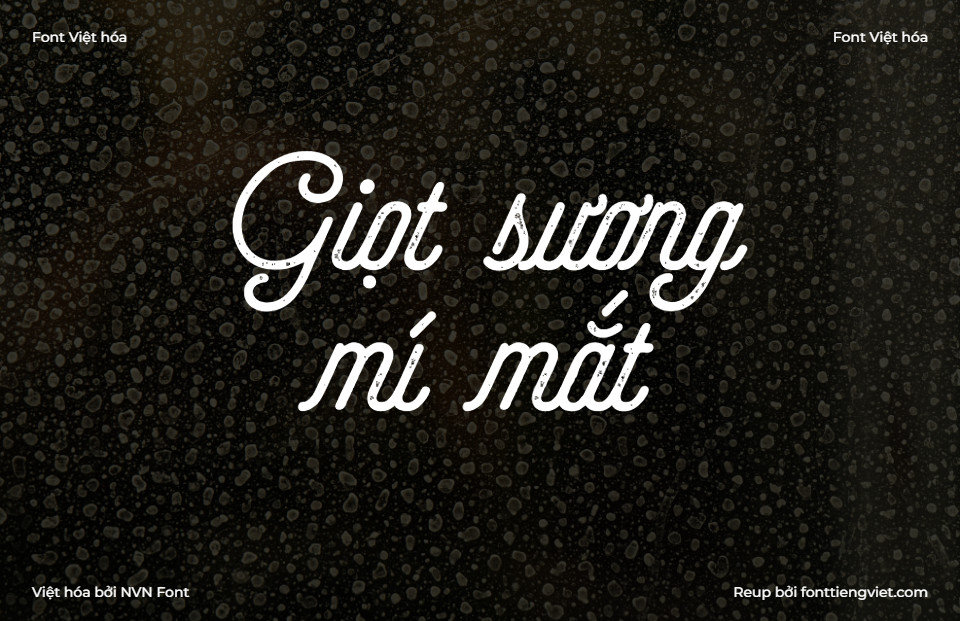
Font Việt hoá NVN Selfie Extra Bold Printed
Font Việt hoá NVN Selfie Extra Bold Printed: Đỉnh cao thiết kế cổ điển và mạnh mẽ
Giới thiệu về Font Việt hoá NVN Selfie Extra Bold Printed
Trong thế giới đồ họa hiện đại, việc tìm kiếm một bộ Font Miễn Phí chất lượng để truyền tải thông điệp là vô cùng quan trọng. Một trong những cái tên nổi bật đang được giới sáng tạo săn đón chính là Font Việt hoá NVN Selfie Extra Bold Printed. Đây là một biến thể đặc biệt thuộc gia đình Selfie, một bộ phông chữ lấy cảm hứng từ những tấm biển quảng cáo cổ điển tại các cửa hàng ở Buenos Aires. Với đường nét dày dặn, chắc chắn nhưng vẫn giữ được sự mềm mại của kiểu chữ viết tay, bộ phông này mang đến một luồng gió mới cho các dự án thiết kế mang phong cách retro và vintage. Điểm đặc biệt của phiên bản “Printed” chính là hiệu ứng nhám bụi bặm, tạo cảm giác như được in ấn trên bề mặt giấy cũ, giúp tác phẩm trở nên chân thực và có chiều sâu hơn bao giờ hết.
Đặc điểm nổi bật của Font Việt hoá NVN Selfie Extra Bold Printed
Phong cách thiết kế độc đáo và ấn tượng
Font Việt hoá NVN Selfie Extra Bold Printed sở hữu độ dày (weight) cực lớn, giúp các con chữ trở nên nổi bật và thu hút thị giác ngay lập tức. Cấu trúc chữ được thiết kế dựa trên các đường hình học mềm mại, tạo nên sự cân bằng hoàn hảo giữa nét mạnh mẽ và sự uyển chuyển. Hiệu ứng kết cấu in ấn (printed texture) được tích hợp sẵn giúp nhà thiết kế tiết kiệm thời gian trong việc tạo hiệu ứng thủ công. Điều này cực kỳ hữu ích khi áp dụng vào các tiêu đề lớn, biển hiệu hoặc các thiết kế áo thun mang hơi hướng đường phố. Sự tinh tế trong từng đường nét giúp phông chữ này không bị thô cứng dù có độ đậm rất cao.
Khả năng tương thích và tối ưu hóa tiếng Việt
Một trong những rào cản lớn nhất khi sử dụng phông chữ quốc tế là lỗi hiển thị dấu tiếng Việt. Tuy nhiên, với Font Việt hoá NVN Selfie Extra Bold Printed, mọi vấn đề đã được giải quyết triệt để. Các dấu thanh được đặt vị trí chuẩn xác, đảm bảo tính thẩm mỹ và sự dễ đọc. Phông chữ này hỗ trợ đầy đủ các ký tự đặc biệt, giúp bạn tự tin thể hiện nội dung mà không lo bị lỗi font. Đây là lựa chọn lý tưởng cho các bạn học sinh, sinh viên làm báo tường điện tử hoặc các giáo viên muốn tạo ra những bài giảng sinh động, bắt mắt trên lớp học.
Ứng dụng thực tế của Font Việt hoá NVN Selfie Extra Bold Printed
Sáng tạo trong quảng cáo và truyền thông
Nhờ vẻ ngoài cá tính, Font Việt hoá NVN Selfie Extra Bold Printed thường xuyên xuất hiện trong các chiến dịch marketing đòi hỏi sự đột phá. Bạn có thể sử dụng nó cho các banner khuyến mãi, poster phim, hoặc bìa album nhạc. Hiệu ứng in ấn của phông chữ tạo ra một cảm giác hoài niệm, gợi nhớ về thập niên 70, 80, rất phù hợp với xu hướng hoài cổ đang quay trở lại mạnh mẽ trong giới trẻ hiện nay. Ngoài ra, việc kết hợp phông chữ này với các tông màu rực rỡ sẽ tạo ra sự tương phản tuyệt vời, giúp thông điệp của bạn đi sâu vào tâm trí khách hàng một cách tự nhiên nhất.
Thiết kế văn phòng phẩm và quà tặng
Nếu bạn đang lên ý tưởng cho một tấm thiệp mời, nhãn dán sản phẩm thủ công hoặc bao bì quà tặng, đừng bỏ qua bộ chữ này. Font Việt hoá NVN Selfie Extra Bold Printed mang lại cảm giác gần gũi và thân thiện, giống như những dòng chữ được viết nắn nót bằng tay nhưng lại chuyên nghiệp hơn. Nó giúp nâng tầm giá trị của món quà, thể hiện sự chỉn chu và gu thẩm mỹ của người tặng. Sự đa dạng trong ứng dụng giúp bộ phông này trở thành công cụ đắc lực cho mọi người dùng.
Kết luận về bộ phông chữ chuyên nghiệp